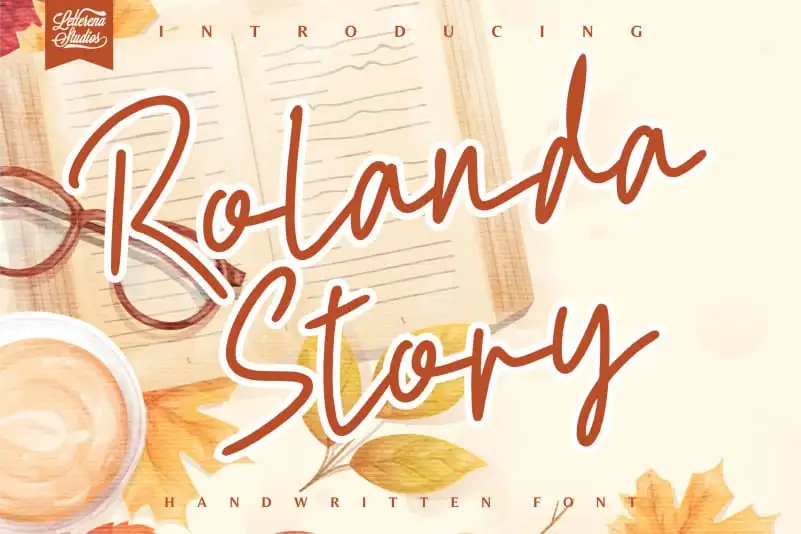
Rolanda Story Handwritten Font
A fonte “Rolanda Story Handwritten Font” é uma escolha ideal para quem procura um traço elegante e casual para suas criações. Desenvolvida pela Letterenastudios, essa fonte é perfeitamente adequada para aplicação em variedades de formatos, desde a identidade visual de seu produto ou marca até os detalhes personalizados como etiquetas ou adesivos. Suas características simples e relaxadas se destacam na criação de anúncios, slogans, logotipos e mensagens de presente, oferecendo um toque pessoal e descontraído a cada projeto. Com sua natureza suave e acolhedora, “Rolanda Story Handwritten Font” é uma opção perfeita para aqueles que buscam um estilo único em seus materiais impressos ou digitais.